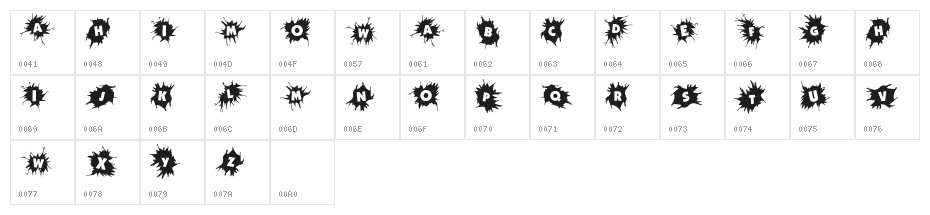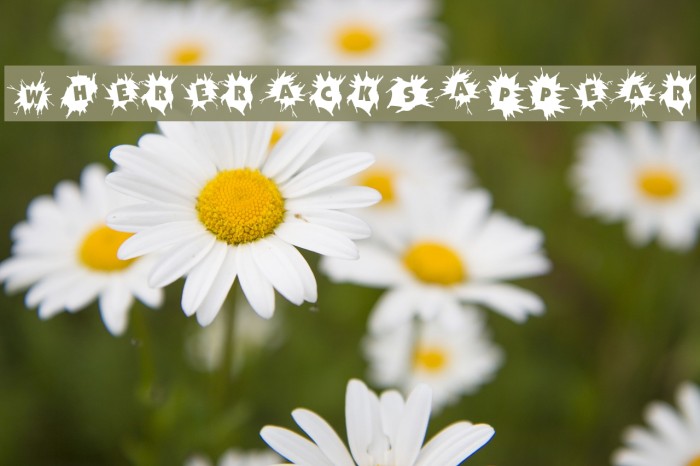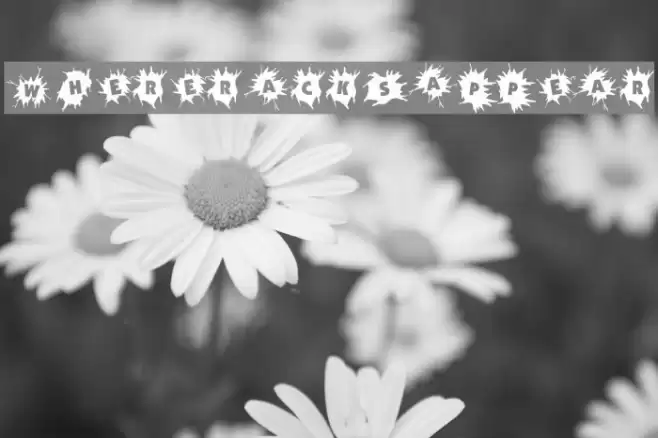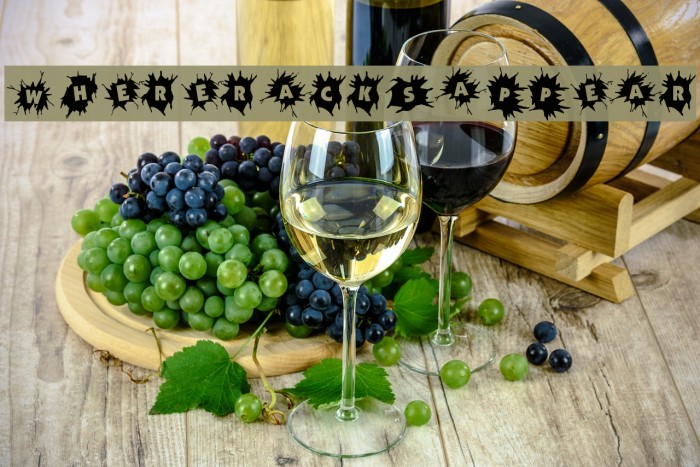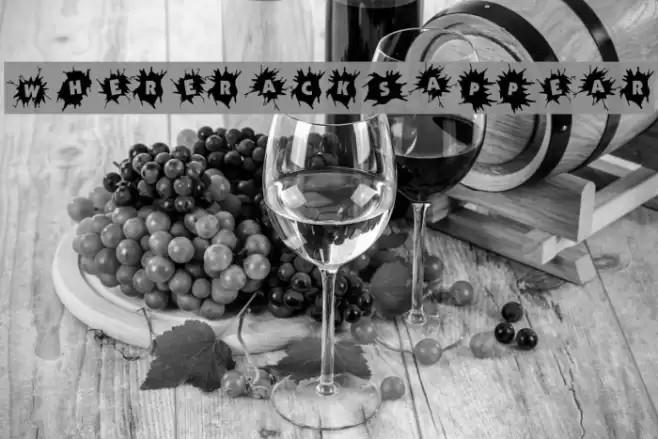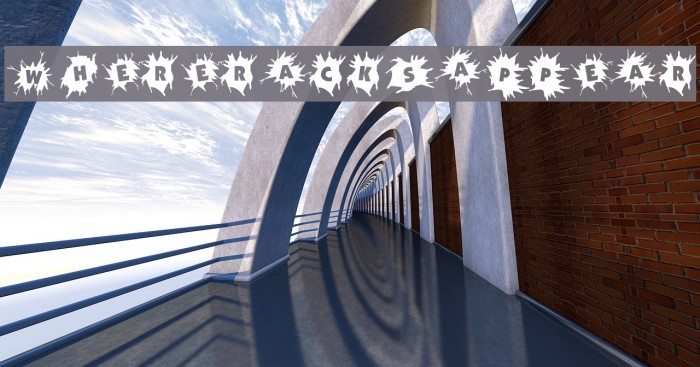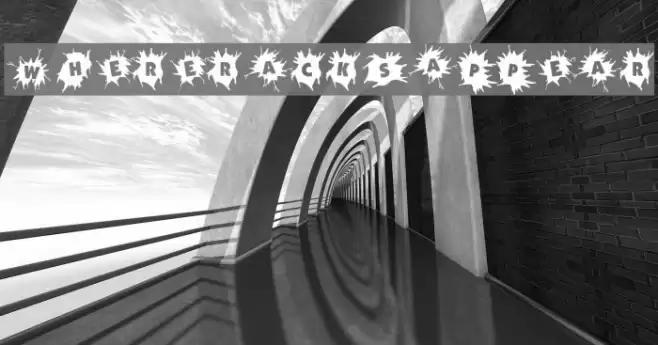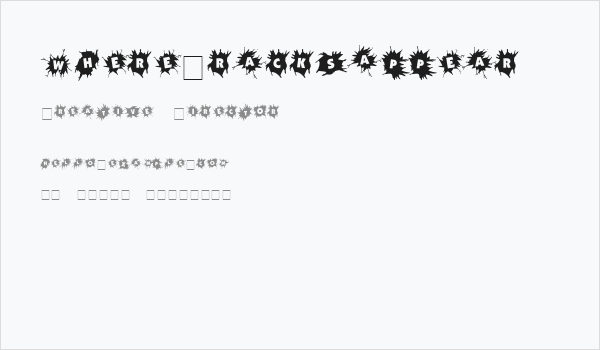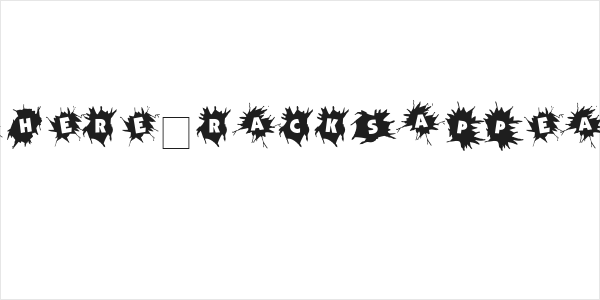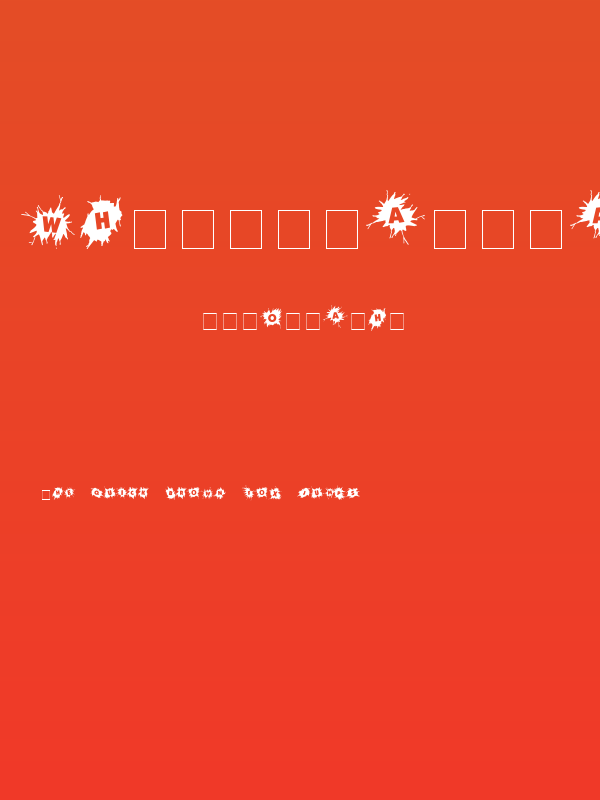
WhereCracksAppear Font
| おすすめプロジェクト | Ideal for use in posters, video game graphics, comic book titles, or any project requiring a dramatic and energetic typeface. |